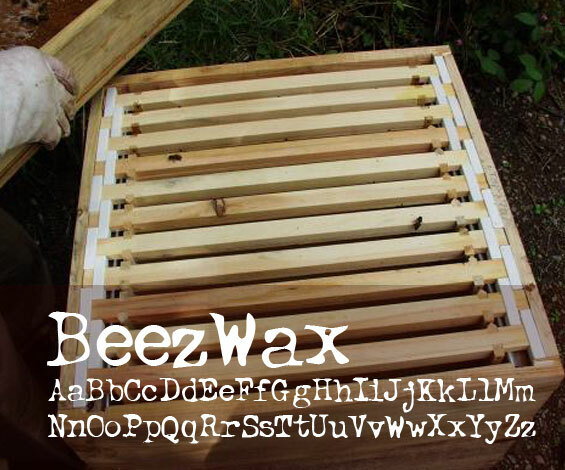
خط BTD BeezWax من تصميم مايكل بريتين (Michael Brittain) من Bigtoedesigns، هو خط عرض مجاني بأسلوب متآكل يبدو وكأنه تُرك تحت أشعة الشمس حتى ذاب وتدلى. الحروف عبارة عن بقع حبر سميكة ذات حواف متعرجة ونقاط مفقودة، مما يمنح كل كلمة طابعاً لزجاً مصنوعاً يدوياً. إنه شعور يجمع بين طابع الجرونج والرسوم المتحركة، وكأنها ضربات فرشاة عشوائية طُبعت في شمع ناعم.
باستخدام BTD BeezWax، ستكتسب عناوينك فوراً طابعاً مرحاً ومخيفاً قليلاً، مما يجعلها بارزة على الملصقات، ودعوات الهالوين، والمجلات، وتصاميم الفرق الموسيقية، وشعارات الألعاب، والتغليف الغريب. يعمل هذا الخط المجاني بشكل أفضل عند استخدامه بحجم كبير، حيث يمكن لمنحنياته المتكتلة وملمسه الخشن أن "تتنفس"؛ قم بإقرانه بخط بلا زوائد (sans serif) بسيط جداً للنص الأساسي، لتبقى هذه الجرأة في مكانها الصحيح - في عناوينك.